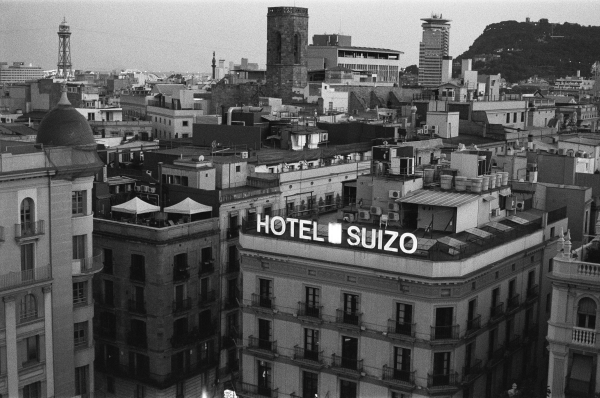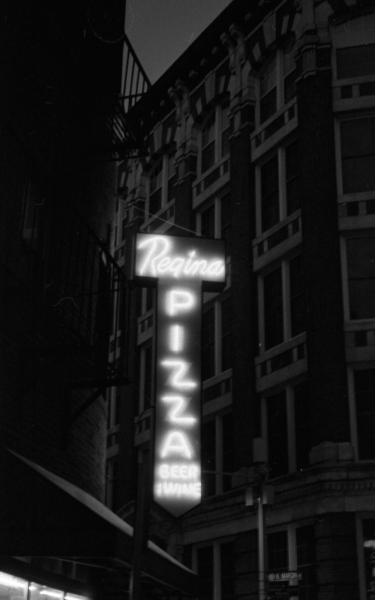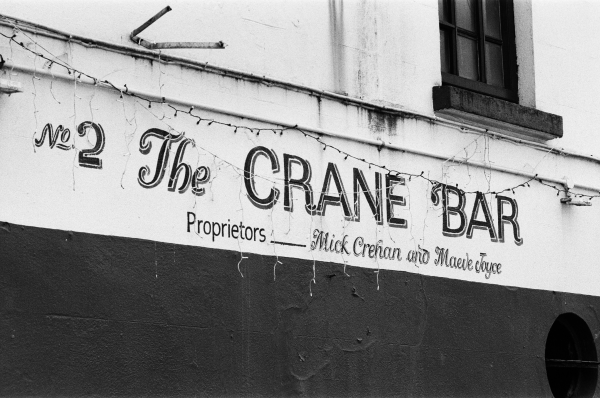
Type Faces: Lernen Sie Jake Murtaugh kennen.
Willkommen zu unserer Reihe Type Faces, in der wir einige der großartigen Persönlichkeiten vorstellen, die bei Monotype hinter der Schrift stehen. Aus aller Welt und aus unterschiedlichsten Bereichen unseres Unternehmens zeigen unsere Kolleginnen und Kollegen eindrucksvoll, dass – wie Charles Nix, Senior Executive Creative Director bei Monotype, es stets formuliert – „Wir sind ALLE kreativ.“
Für Jake Murtaugh ist klar, was seine Arbeit bei Monotype so besonders macht: „Ich darf den ganzen Tag wunderschöne Dinge betrachten.“ Als Digital Operations Manager arbeitet er an der Schnittstelle von Design, Technologie und Storytelling. Er ist kein Entwickler, beschäftigt sich aber mit Code. Er ist kein Designer, trägt jedoch dazu bei, wie Monotype-Schriften online wahrgenommen und erlebt werden. Diese Rolle verschafft ihm einen umfassenden Blick auf das Unternehmen – und ermöglicht es ihm zugleich, die Kunst der Typografie jeden Tag neu zu würdigen. Lesen Sie weiter, um mehr über Jake zu erfahren.
Porträt von Jake. Foto: Simon Simard.
Welche Rolle spielt Kreativität in Ihrem Leben?
Ich fotografiere analog. Inzwischen besitze ich etwa 40 Kameras. Was während der Pandemie als Ausgleich für die mentale Gesundheit begann, entwickelte sich zu einer echten Leidenschaft – und zu einer beachtlichen Sammlung. Eine meiner Lieblingskameras ist ein Messsuchermodell, das ich in Shoreditch gekauft habe, nachdem meine Kamera auf einer Reise ins Londoner Büro kaputtgegangen war.
Eines der ersten Fotos, die Jake in London mit seiner neuen Kamera aufgenommen hat. Foto: Jake Murtaugh.
Fotografie bringt mich aus dem Haus, lässt mich reisen und macht mich neugierig auf neue Orte und Entdeckungen. Ich lebe in Salem, Massachusetts, das ein bisschen wie eine kleine Künstlerkolonie ist. Jede Woche besuche ich einen Dunkelkammerkurs an der Salem State University.
Was schätzen Sie am Leben in Salem?
Es ist inklusiv. Es ist einladend. Es fühlt sich wie ein Dorf an. Man kennt die Menschen, denen man begegnet, und gleichzeitig hat die Stadt eine lebendige Energie. Kunst und Gemeinschaft spielen eine zentrale Rolle – und das bedeutet mir viel.
Der Leuchtturm von Salem. Foto von Jake Murtaugh.
Vor Monotype war ich im Bereich der Öffentlichkeitsarbeit tätig – mit Schwerpunkt auf der psychischen Gesundheit von Kindern und der Reform des Pflegewesens. Heute bin ich Mitglied im Massachusetts Family Advisory Committee. Ich glaube, es gibt kaum eine bessere Möglichkeit, sich für die eigene Gemeinschaft einzusetzen, als Kinder und Familien zu unterstützen.
Auch wenn ich heute in einem ganz anderen beruflichen Feld tätig bin, suche ich weiterhin nach Wegen, meine Arbeit mit der Gemeinschaft zu verbinden. Und ich denke, dass auch Schriften dazu beitragen können, Menschen zu stärken und zu verbinden.
Jake glaubt, dass starke Gemeinschaften durch Verbindung entstehen. Foto von Jake Murtaugh.
Wie verbinden Fonts Ihrer Meinung nach Menschen?
Fonts sind mehr als nur Worte. Sie erzählen eine Geschichte, unterstützen eine Botschaft oder wecken Erinnerungen und Gefühle. Sie sehen eine bestimmte Schrift und denken an Weihnachten. Eine andere erinnert Sie sofort an Halloween. Es ist ein visuelles Signal, fast augenblicklich – ganz unabhängig davon, was die Wörter selbst sagen.
Und genau dieses Gleichgewicht zwischen Emotion und Zugänglichkeit, zwischen Regelbruch und dennoch funktionierender Gestaltung – das macht Fonts wirklich interessant.
Die Typografie der Crane Bar setzt sofort die Stimmung. Foto von Jake Murtaugh.
Kürzlich haben wir gemeinsam mit der Obama Foundation eine Fallstudie zur Entwicklung der Gotham veröffentlicht – ein konkretes Beispiel dafür, wie Fonts für gesellschaftliches Engagement eingesetzt werden können. Hinter der Entscheidung, wie und wo unterschiedliche Varianten der Schrift verwendet werden, steckte viel Überlegung und klare Intention, um Themen wie Demokratie und gesellschaftliche Teilhabe zu vermitteln.
Sentinel, eine von Jakes Lieblingsschriften.
Haben Sie eine Lieblingsschrift?
Ich mag kräftige Schriftschnitte wie Neue Haas Grotesk Black oder Sentinel Black. Ich liebe Schriften, die für H1-Überschriften eingesetzt werden. Sie sind eindrucksvoll. Sie wollen gesehen werden. Sie schreien ein bisschen. Sie setzen ein starkes Statement!
In Jakes Fotografie ist Typografie Teil der Szene – und oft sogar der Blickfang. Foto von Jake Murtaugh.
Was ist Ihre Rolle bei Monotype?
Ich bin Digital Operations Manager. Das bedeutet, dass ich unsere Websites und weiteren digitalen Plattformen mitverantworte. Ich beaufsichtige das Content- und Digital-Experience-Management und arbeite produkt-, marketing- und strategieübergreifend.
Die Rolle ist sowohl kreativ als auch operativ. Ich habe die Freiheit, gestalterische Entscheidungen zu treffen – insbesondere in Bezug auf Bildwelt und Inhalte. Jeden Tag darf ich mir wunderschöne Arbeiten unglaublich talentierter Menschen ansehen.
Digital Operations Manager
Jake Murtaugh.
Jake Murtaugh is Digital Operations Manager at Monotype. Jake's work sits at the intersection of design, technology, and storytelling. In this role, he helps manage Monotype's websites and other digital properties, oversees content and digital experience management, and works across product, marketing, and strategy.
Photo by Ben Flythe.